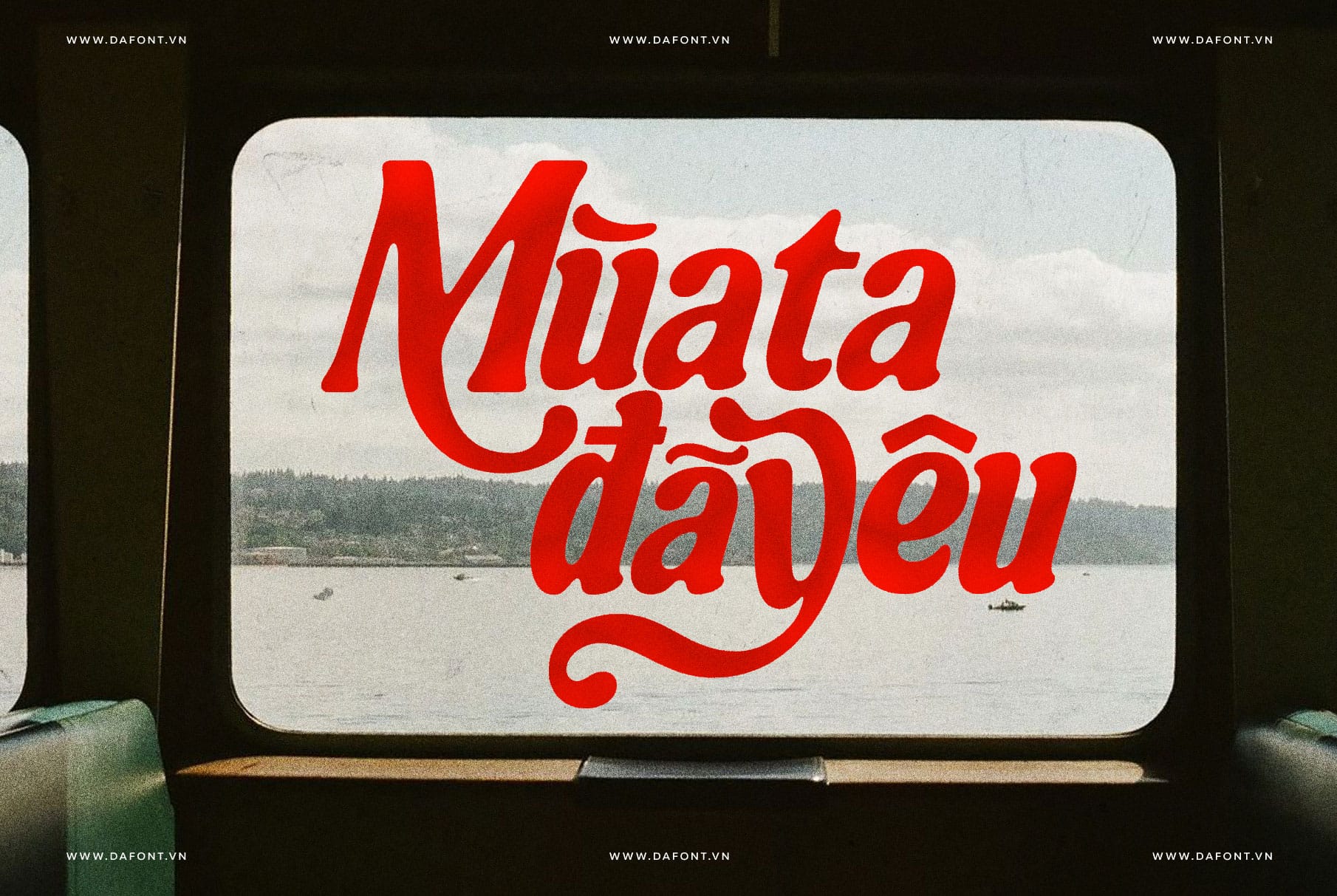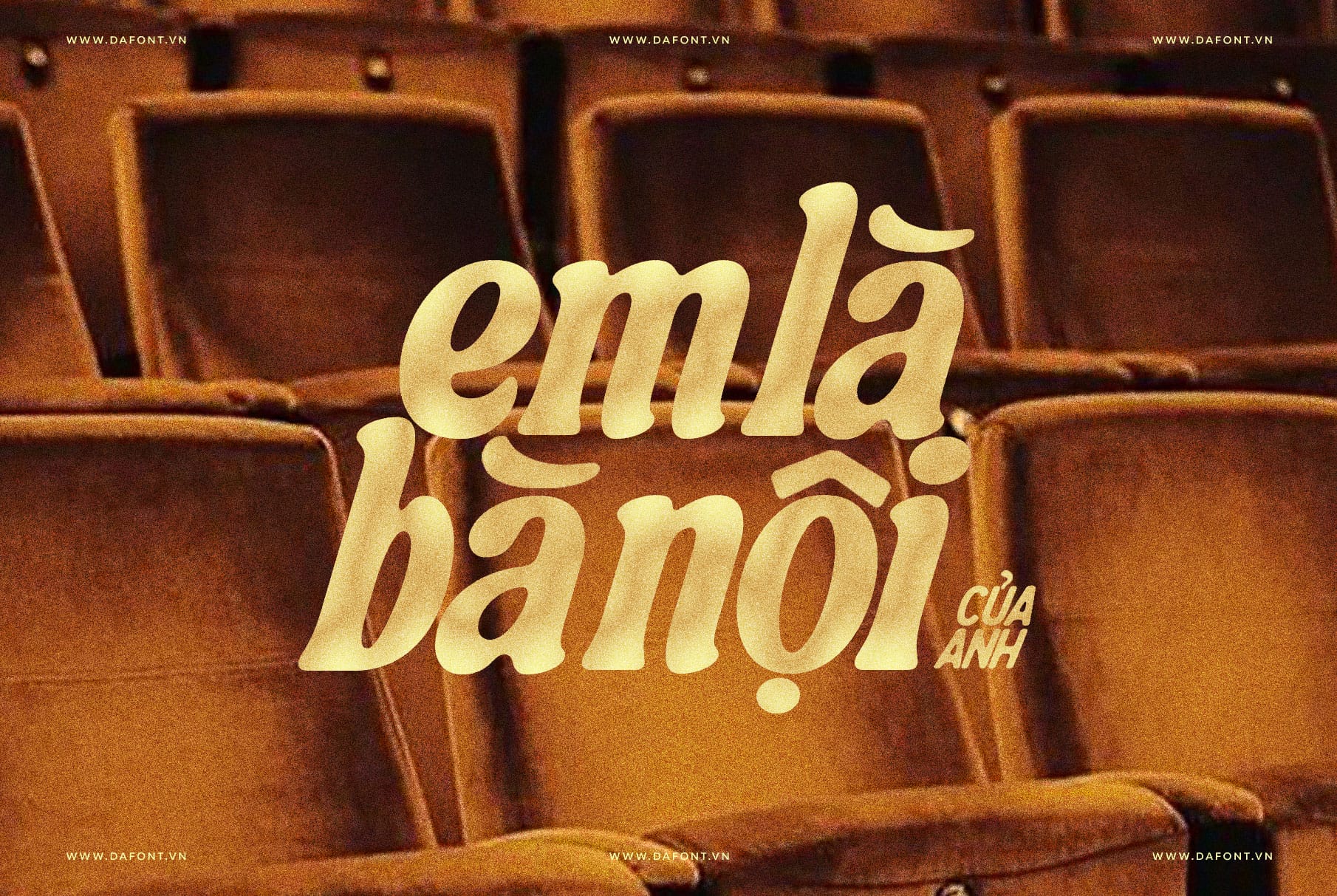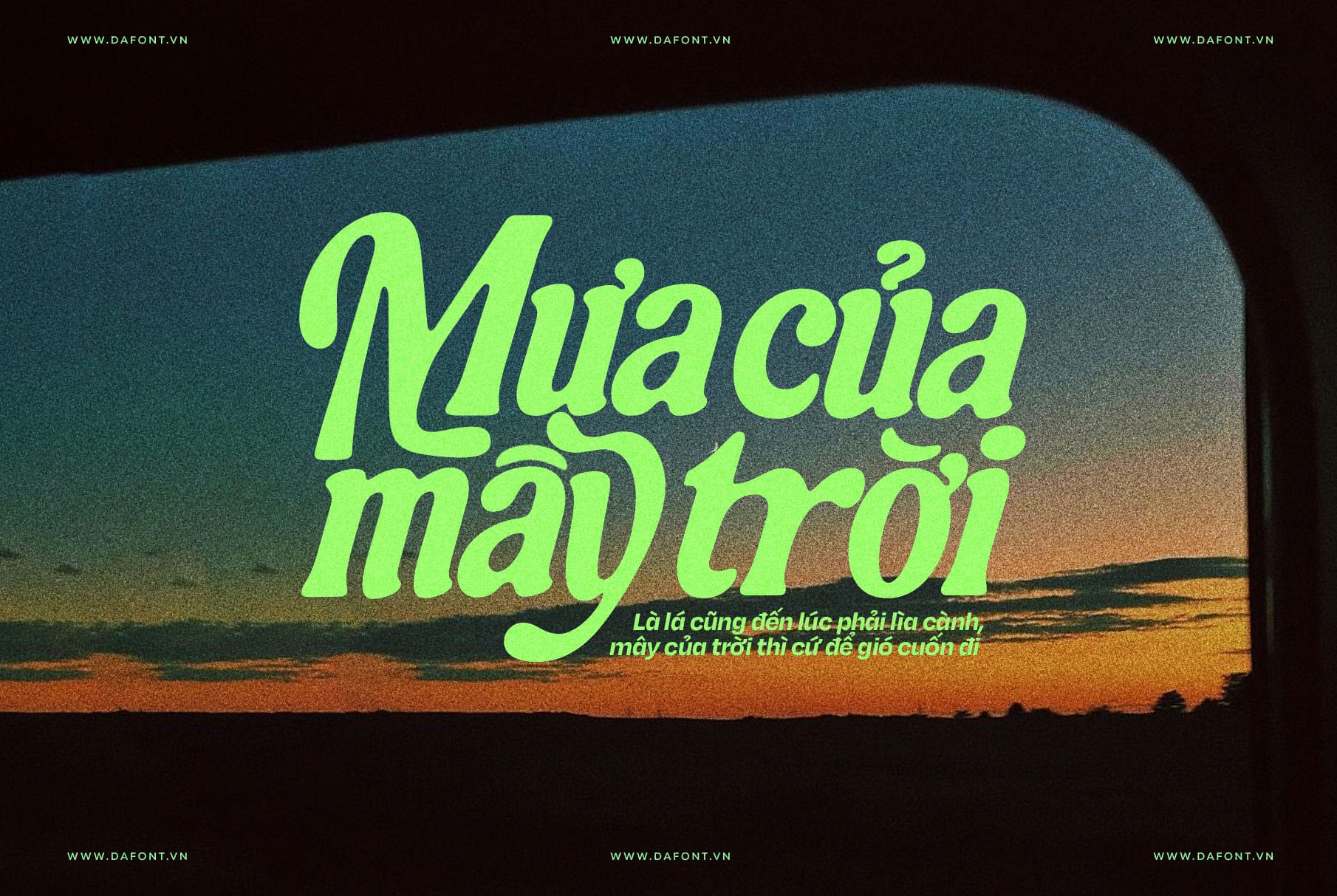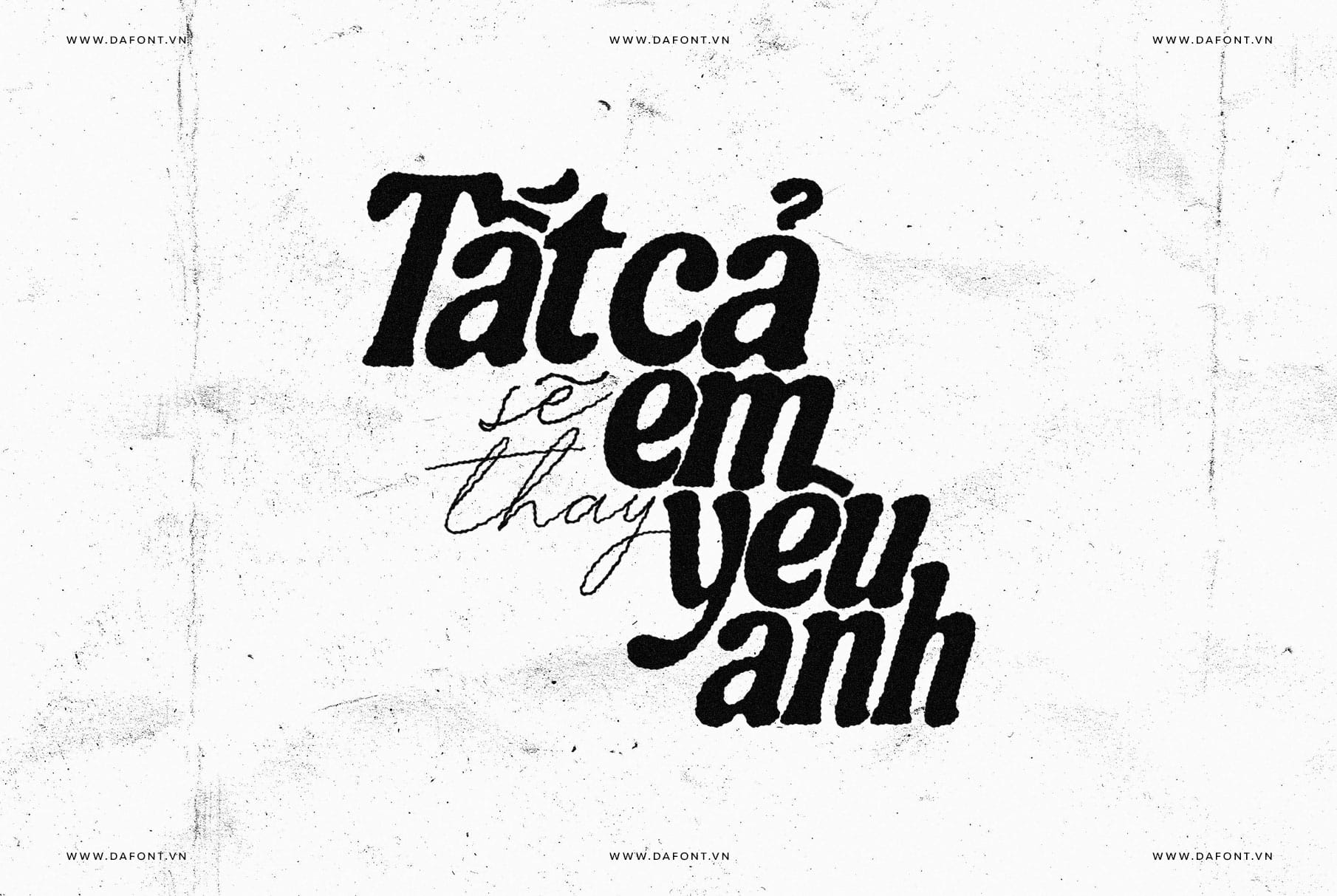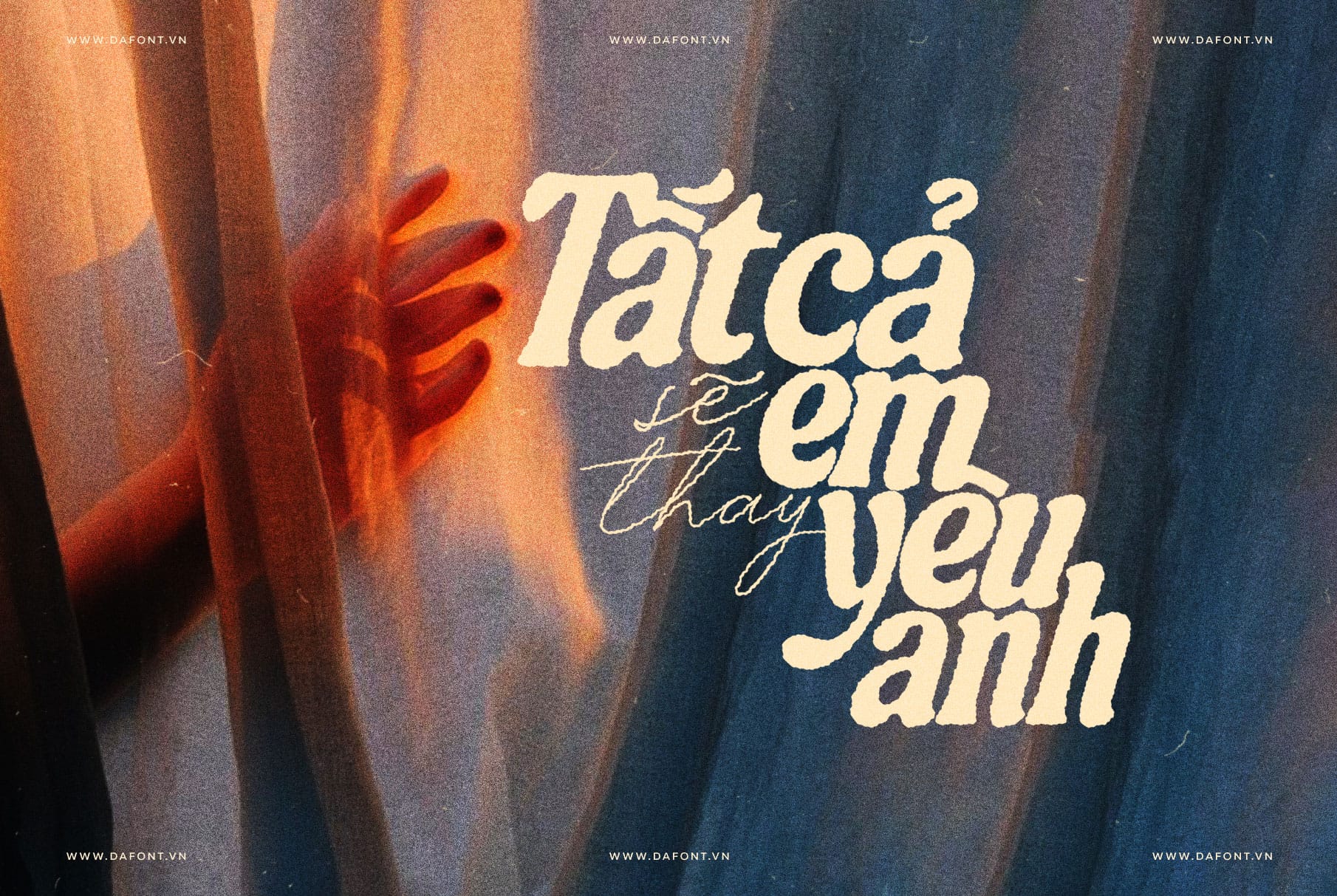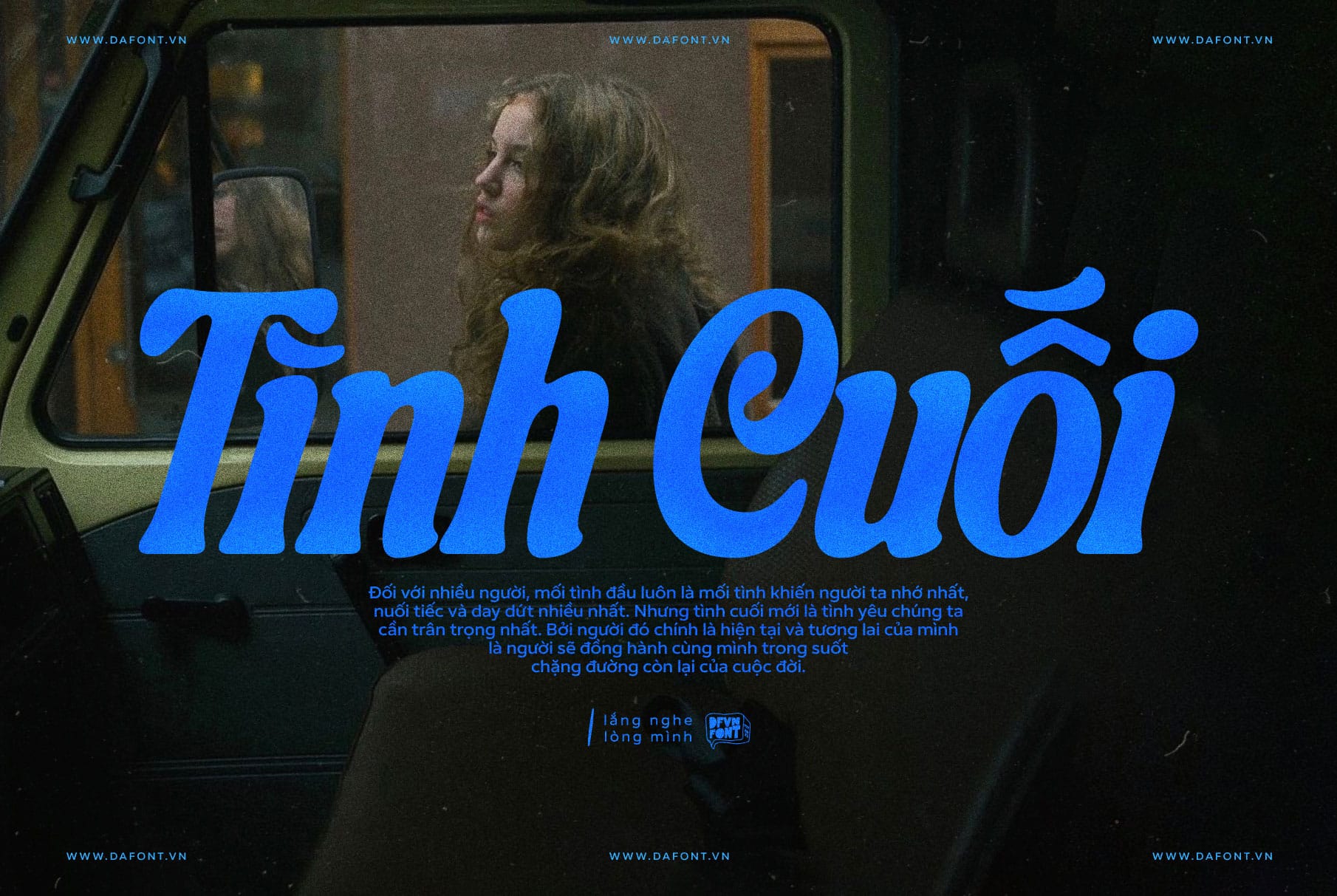
DFVN TAN – SUNSET font là một kiểu chữ serif được lấy cảm hứng từ sự ngọt ngào của những ngày hè kéo dài. Với nét chữ được thiết kế đậm kết hợp với đường cong quyến rũ và đầy sức sống, font này mang đến cảm giác thoải mái, vô tư như đang thư giãn bên bờ biển.
TAN – SUNSET đem lại “vibe” mùa hè đúng nghĩa: nét bút dày, đường cong phóng khoáng khiến tiêu đề nổi bật nhưng vẫn thân thiện, đủ “ngọt” cho wedding & lifestyle, đủ “đậm” cho branding F&B/retail. Tính “dễ đọc ở cỡ vừa–lớn” giúp bạn dùng làm headline, logo, tagline mà không bị rối mắt.
Đặc điểm nổi bật
Không chỉ đẹp mắt, DFVN TAN - SUNSET còn sở hữu nhiều tính năng kỹ thuật ấn tượng, giúp nó nổi bật giữa hàng ngàn font chữ khác:
• Phong cách thiết kế: Nét chữ đậm kết hợp với đường cong quyến rũ, tạo nên sự cân bằng giữa sự kỳ quặc và mạnh mẽ, đơn giản mà phong cách. Font gợi lên hình ảnh nắng vàng, sóng biển và những kỷ niệm hè đáng nhớ.
• Tính năng OpenType: Hỗ trợ ligatures, alternate characters và hơn 200 glyphs bổ sung trong phiên bản Việt hóa. Kerning đầy đủ đảm bảo chữ cái kết hợp mượt mà, đặc biệt với tiếng Việt.
• Dễ đọc ở cỡ lớn như tiêu đề/logo: Với nét chữ đậm, dày vì vậy lý tưởng cho headline/wordmark, không phù hợp với văn bản dài.
• Dễ dàng kết hợp nhiều font khác: Kết hợp sans-serif trung tính cho body để giữ độ đọc và tương phản. Có thể phối serif thanh lịch cho tagline phụ nhằm tạo chiều sâu và cảm giác thủ công.
DFVN TAN - SUNSET phù hợp cho nhiều thiết kế
Font TAN - SUNSET cực kỳ linh hoạt, phù hợp với nhiều lĩnh vực thiết kế. Dưới đây là một số ứng dụng phổ biến:
• Branding và Logo: Thêm sự tươi mới cho thương hiệu thời trang hè, quán cà phê ven biển hoặc sản phẩm lối sống.
• Packaging và Poster: Lý tưởng cho bao bì sản phẩm mùa hè, poster sự kiện hoặc trích dẫn motivational với vibe hoài niệm.
• Mạng xã hội và Invitations: Phù hợp sử dụng làm tiêu đề cho nội dung trên Instagram, Facebook, Tiktok, lời mời đám cưới hoặc nội dung social media cần sự vui vẻ, dễ đọc.
• Dự án Lifestyle: Hoàn hảo cho thiết kế liên quan đến du lịch, ẩm thực hoặc sự kiện ngoài trời, mang lại cảm giác "seaside elegance".
Designer có thể kết hợp font này với màu sắc rực rỡ như xanh, cam, vàng sunset để tăng tính thẩm mỹ giống như hình ảnh demo font này trên DFVN sẽ giúp dự án của bạn trở nên "sống động và cá tính" hơn bao giờ hết.
Hãy để Sunset mang chút nắng, chút lấp lánh và cả cá tính vào những dự án sáng tạo của bạn. Không chỉ là một font chữ — đó là ký ức mùa hè bạn có thể mang theo bên mình qua mỗi mùa.